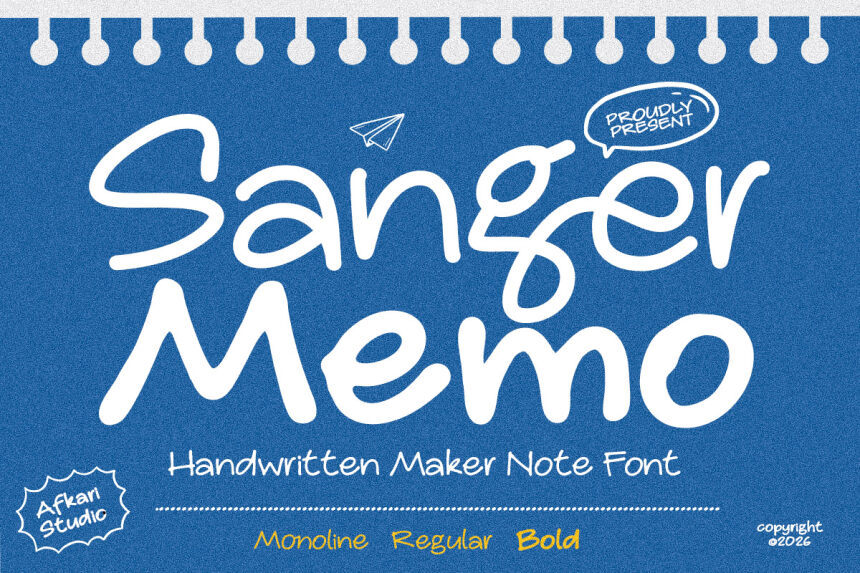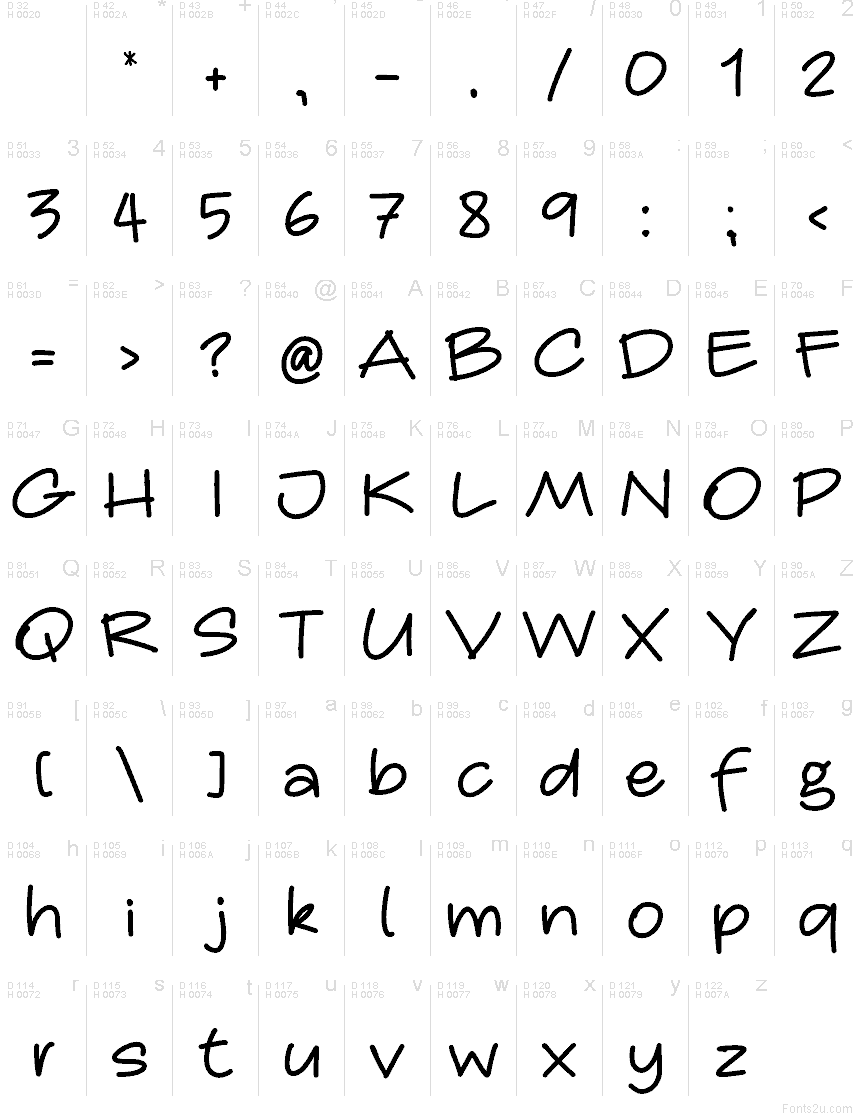
Sanger Memo Monoline od Afkari Studio to darmowy, odręczny krój monoline, który oddaje swobodę notatek pisanych na szybko markerem. Litery poruszają się w jednym, stałym rytmie, z zaokrąglonymi kształtami i lekką nieregularnością, dzięki czemu całość wydaje się naturalna i bezpośrednia, a nie wygładzona.
Sprawia to, że krój świetnie pasuje do brandingu kawiarni, przyjaznych opakowań, cytatów w stylu scrapbooku, nagłówków na plakaty czy grafik w mediach społecznościowych, gdzie darmowy font powinien od razu budzić ludzkie skojarzenia. Sprawdzi się też w krótkich tekstach i luźnych logotypach, ponieważ prosta grubość linii pozwala, by to odręczny charakter grał pierwsze skrzypce.